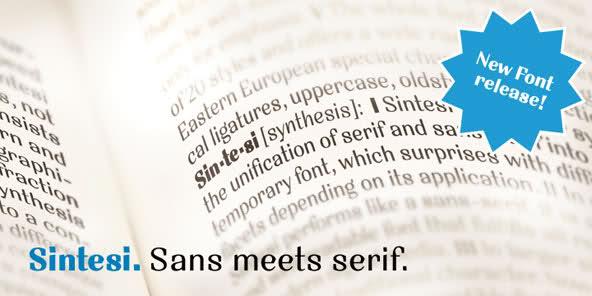
Sintesi. Serifenlose trifft auf Serifen.
Sie möchten eine zeitgemässen Schrift und dabei gleichzeitig Tradition ausdrücken? Dann ist Sintesi die richtige Wahl für Sie.
Sintesi steht für Synthese. Hier vereint sich eine Serifenschrift mit der Serifenlosen in einer zeitgemässen Gattung, die je nach Anwendung mit verschiedenen Facetten überrascht.
In Lesegrösse verhält sich Sintesi wie eine Serifenlose. Sie ist kompakt, gut lesbar und besteht allen Anforderungen der heutigen digitalen Medien.
Bei grösseren Schriftgraden entfaltet sie ihren traditionellen Charakter. Nun kommen ihr starker Strichkontrast und der spürbare Feder-Duktus voll zur Geltung, wie es sich für eine geschichtlich verwurzelte Antiqua gehört.
Ergänzt wird die Schrift durch eine passende Kursive. Da ihr Kursivcharakter hauptsächlich von der Schreibgeschwindigkeit und weniger von der moderaten Schriftlage stammt, kann sie zu weit mehr als nur zu Hervorhebungszwecken eingesetzt werden.
Die gesamte Schriftfamilie umfasst 20 Schriftschnitte und bietet eine breite Auswahl an West- und Osteuropäische Sonderzeichen, Ligaturen, Versal-, Mediäval- und Bruchziffern.